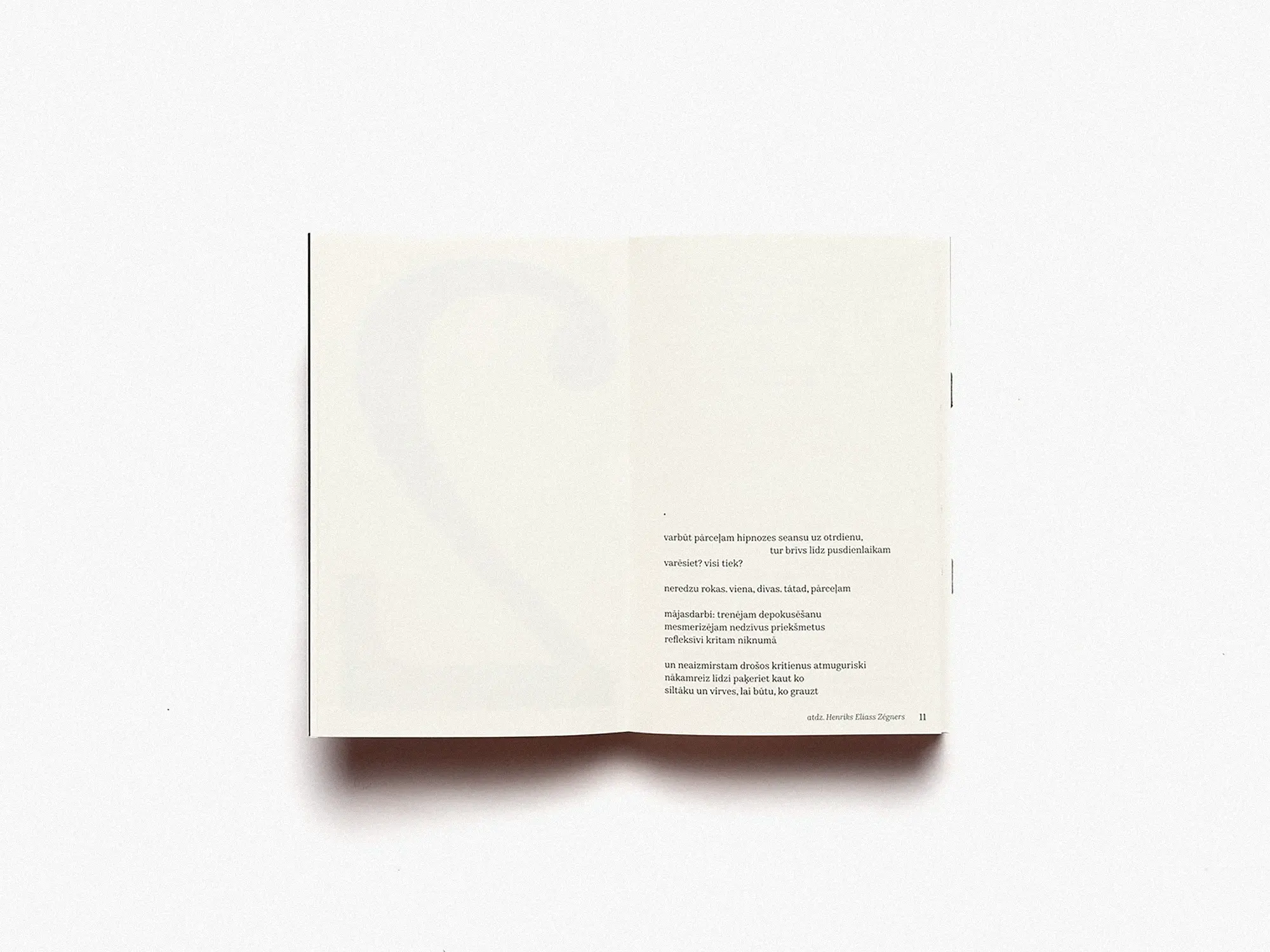
В конце 2024 года в рижском издательстве talka books вышел двуязычный поэтический сборник участника текст-группы «Орбита» Семёна Ханина. За типографику на обоих
Kazimir Text — текстовая версия заголовочного Kazimir, переосмысляющего книжную типографику конца XIX века. По сравнению с Kazimir у текстового шрифта более широкие пропорции, уменьшенный контраст и сильно расширенная кодовая таблица, а ещё значительно больше вариантов насыщенностей.